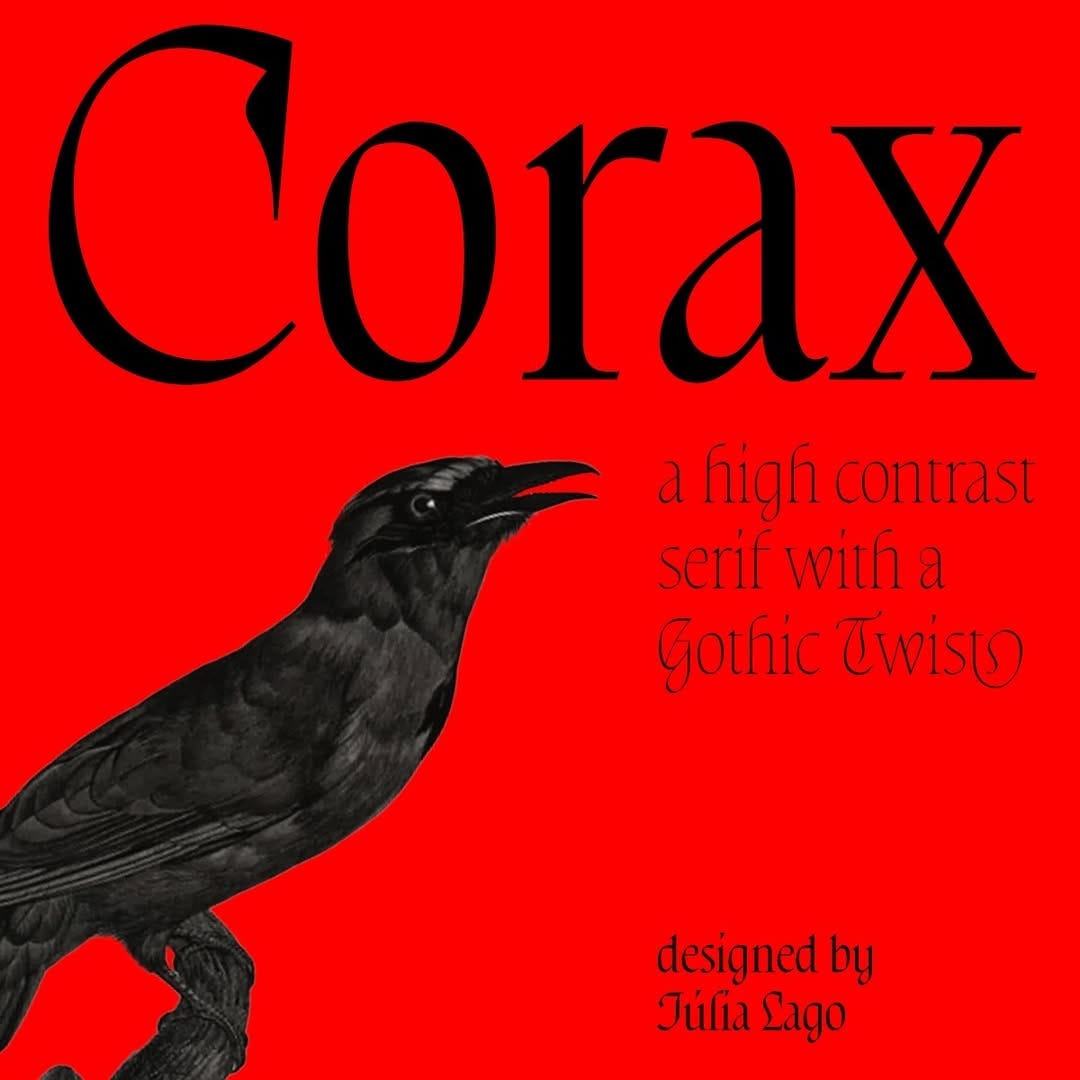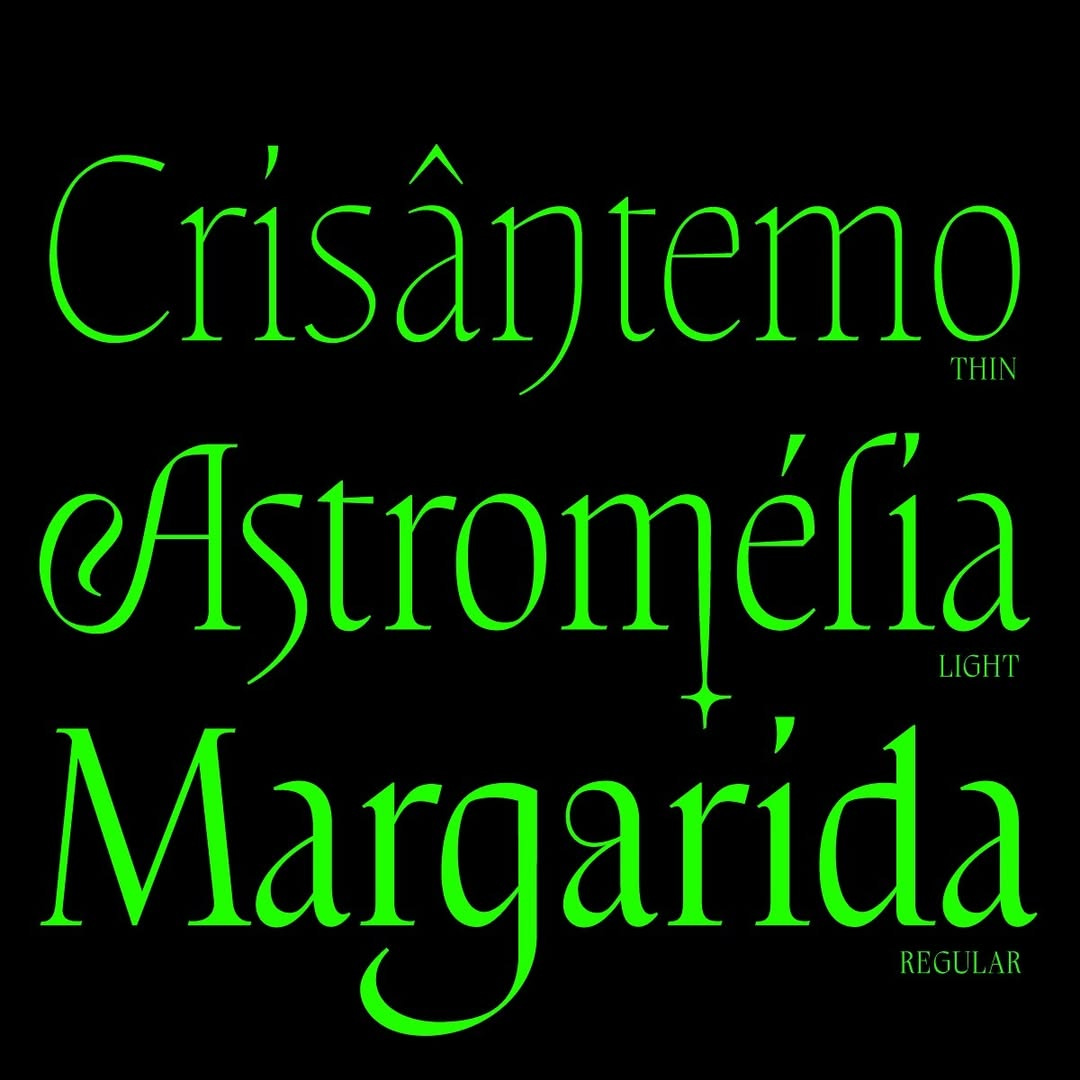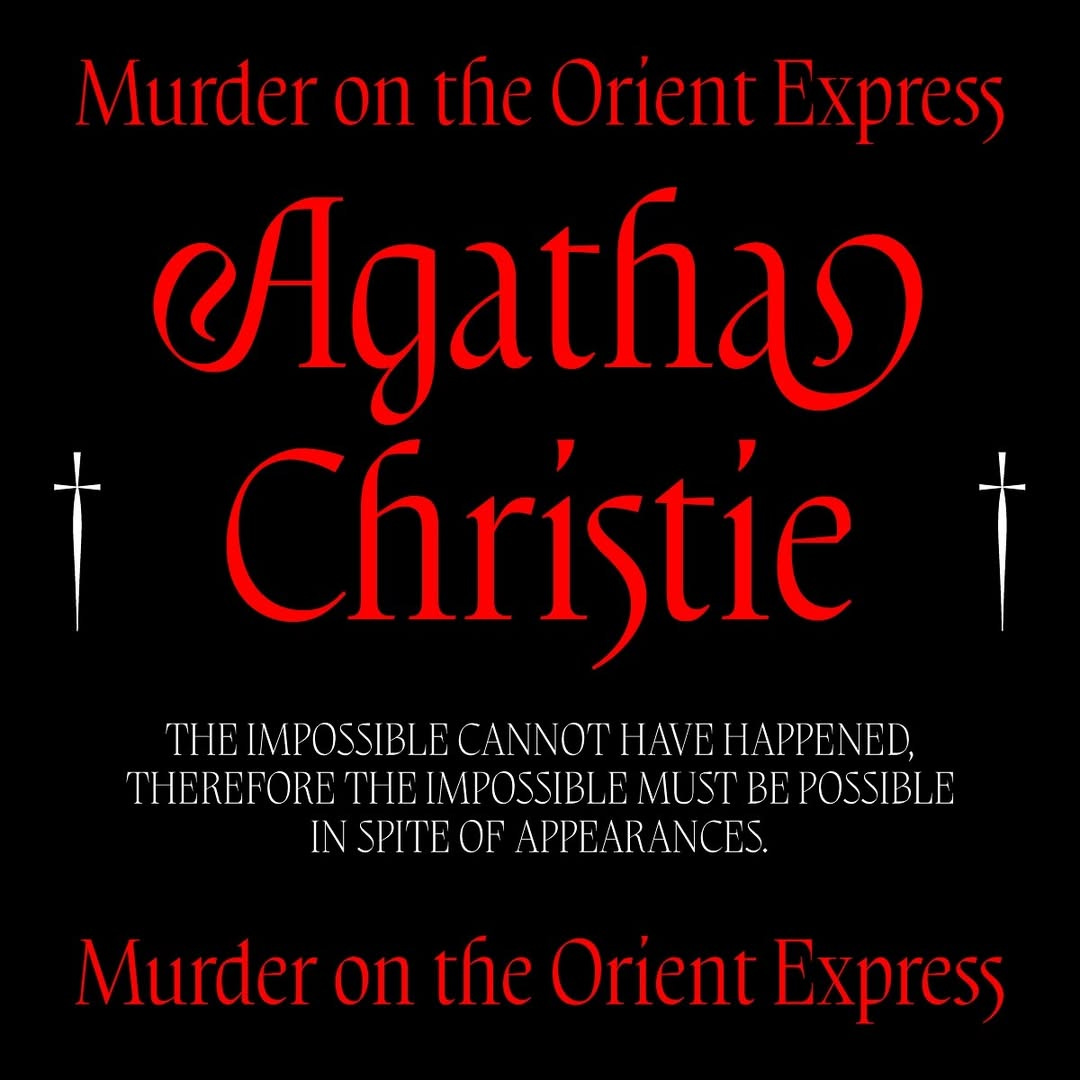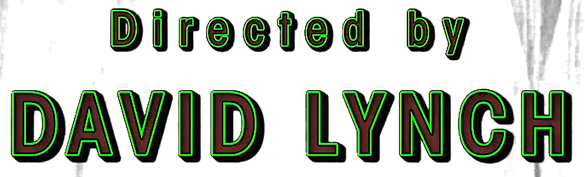
2024 foi um ano intenso. Qualquer coisa entre janeiro e novembro parece que aconteceu antes da pandemia, e que todo mundo precisou dobrar a dose de cafeína, surfar burnoutinhos e torcer pra chegar vivo. Tanto que o balanço de fim de ano do Tipo Aquilo teve que esperar 2025 pra acontecer, porque até dezembro este que vos redige estava fazendo uma penca de coisas ao mesmo tempo.
Como os mais longevos dessa freguesia sabem, a última edição do ano é dedicada ao momento tipográfico… o hit feito de letras que pegou o mundo em cheio por algum motivo. Só que 2024 foi um ano meio fraco nesse sentido. Talvez as IA's generativas tenham uma parcela de culpa nisso; não por elas trabalharem mal com texto, mas sim porque ficou fácil para as pessoas tirarem do texto a função de comunicar com precisão. A surra de eventos acontecendo o tempo todo em todo canto também fez ficar difícil determinar apenas um momento em que a tipografia se sobressaísse como um meme ou algo significativo.
O que não quer dizer que não temos algo…
A capa do álbum “Brat”, da Charli XCX, é o que ficou mais próximo de um meme tipográfico, reproduzido de uma penca de formas diferentes não só pela Internet em si, mas pela própria Charli. O estilo de falso pixelado/estourado com Arial Narrow num fundo verde-limão, desenvolvido ao longo de cinco meses por Brent David Freaney, foi remixado de tantas formas, com tantas conotações, que pintou a vida online de verde e facilmente é o momento tipográfico de 2024.
Eu sei que vocês conseguem pensar em um monte de capas de álbum mais bonitas, mais transudas, mais qualquer-coisa do que essa. Pra mim, ela representa um cansaço da nostalgia. Nos últimos anos, um monte de artistas revisitaram o século passado e até os anos 2000 em suas músicas, clipes e artes de álbum, buscando a beleza perdida dessas décadas. A Charli, por sua vez, não teve vergonha de abraçar o “feio”, o esquisito, o não-polido contemporâneo, e meter o verde-limão (e, depois, o branco) por aí. Poucas coisas são tão brat quanto isso. Até o próprio conceito de brat teve seus remixes, com as pessoas descobrindo-se brats em algum ponto. Até a então candidata à presidência dos EUA Kamala Harris foi tida como brat.
(e não sou eu quem vai te explicar o que é “brat”, pergunte ao seu entendedor de cultura pop mais próximo)
Pra 2025, fica uma promessa: eu vou falar um pouco do David Lynch. Ele está aqui nesta edição mais como uma homenagem póstuma do que como um meme de 2024. Contudo, não se engane quanto a isso: os letterings característicos da série, em Avant Garde Condensed com borda verde, aparecem com recorrência nos últimos anos, conforme a própria série e toda a filmografia do diretor surgem em listas de discussão e feeds por aí como eventos bem localizados de distorção da realidade. Lynch não tinha uma relação tão íntima com alguma fonte como outros diretores, mas ele é um ótimo ponto de partida para falar sobre a presença de texto em cena e o quanto ela afeta a própria percepção e sensação do espectador.
Lynch sustentava que “As palavras mudam a forma com que você percebe o que está acontecendo na cena. E são um ótimo contra-peso para outras coisas acontecendo.” Essa frase é um ponto de partida sensacional para muita coisa sobre design, escrita, audio-visual e um monte de coisas mais, mas vai ficar pro tempo certo. Por enquanto, guardemos como uma singela homenagem, e/ou um sinal de que as coisas só fazem sentido quando esse lettering aparece e exclui a necessidade das coisas fazerem sentido.
Os números absolutos mostram um crescimento na produção dessa newsletter, e quero manter esse ritmo… ainda mais com uma centésima edição vindo (e eu não faço ideia de um bom tema pra esse evento). Pra manter esse ritmo, eu preciso parar por um tempinho, até março, pra terminar várias coisas pendentes, descansar um pouco e pensar nas pautas deste ano, na minha foundry em gestação, e de como o Tipo Aquilo ficará alinhado nesse contexto. Já tem texto deste semestre escrito, mas tudo precisa do tempo certo.
Até lá, vocês podem conferir minha entrevista para o Rodrigo Ghedin, do Manual do Usuário, em que eu conto um pouco de como isso surgiu e como cada edição acontece no seu tempo. Ainda sobre a troca de cartas entre newsletters, vale a pena conferir o texto do
no sobre Linguagem Simples, em resposta à minha edição sobre o tema. De fato, foi um dos temas que eu mais gostei de ter escrito, e a carta do Júnior me deu a mesma alegria.Linguagem Simples, Machado de Assis, rodovias, Garamont, Globo, greves de tipógrafos… eu não sei dizer sobre qual desses assuntos eu mais fiquei satisfeito em ter escrito. A edição sobre Ziraldo é, de longe, a mais “popular” em likes e compartilhamentos, e colocou o Tipo Aquilo no radar de muita gente legal que eu sequer tenho roupa para estar perto. Ainda há mais para se falar sobre Ziraldo, e eu pretendo fazer isso nesse ano, junto com mais histórias, mais didática, mais personagens e mais letras bonitas.
🎥 Vídeo: brat but it's a graphic design analysis, (em inglês) uma análise do design gráfico do álbum de Charli XCX por Linus Bowman.
🔗 Link: Brat Generator, um gerador de memes baseado no lettering do álbum “Brat”, da Charli XCX.
🇧🇷 Fonte brazuca: Corax, de Júlia Lago.